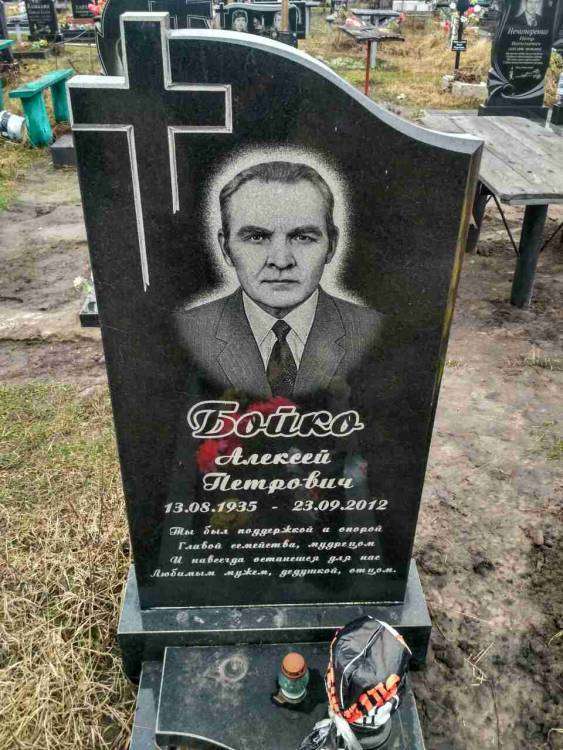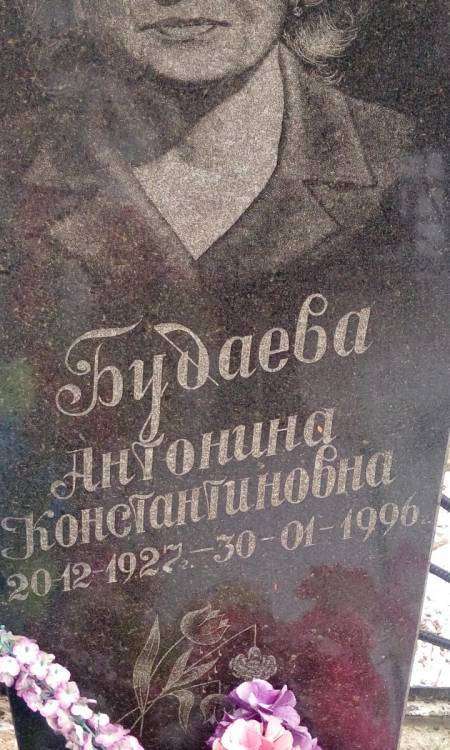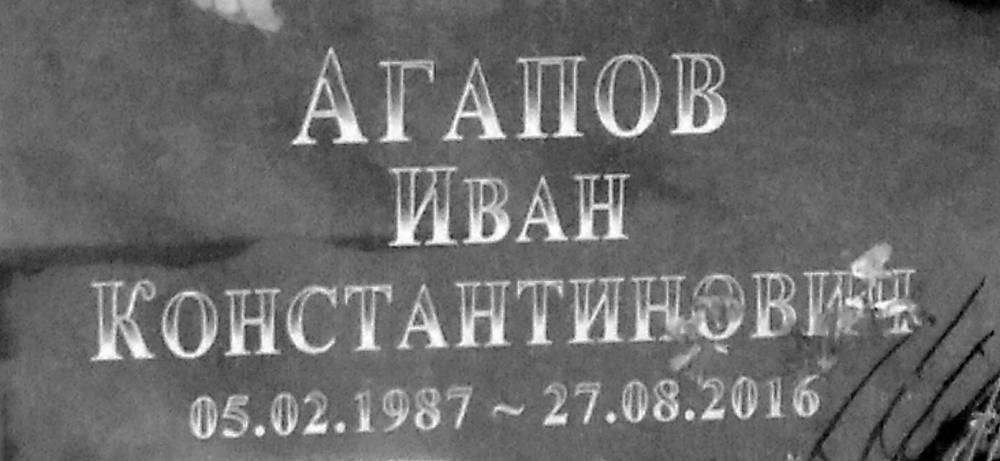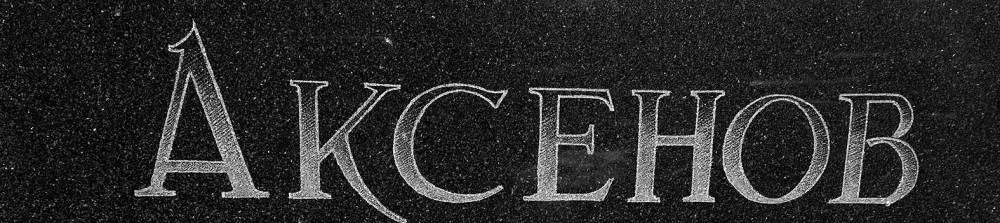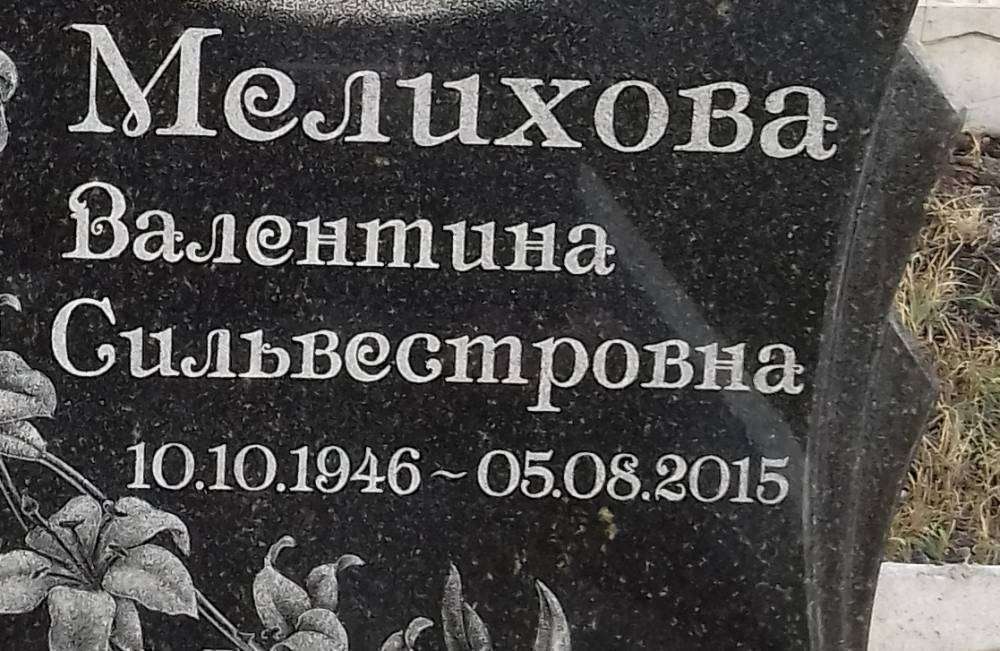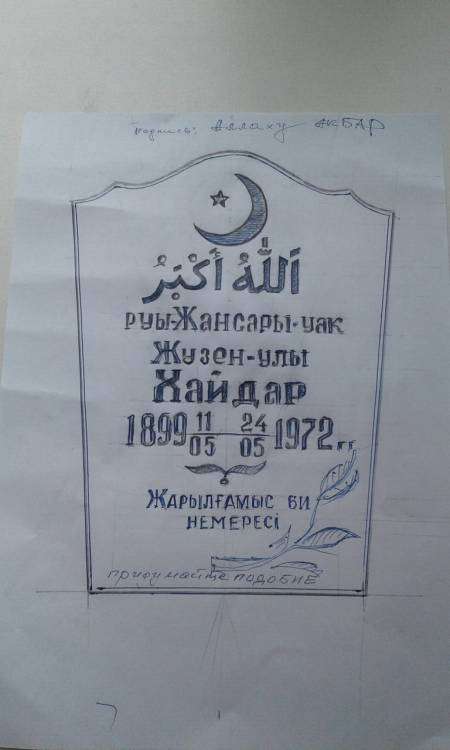
Помогите найти шрифт!
Саид держите нашёл
1Isadora M Bold
Но форум читать надо. Яша уже давным-давно ответил
Выручайте коллеги!
Похож, но не он. Сам весь вечер лопатил сеть. Походу это ручной.
Подскажите кто знает? Что за шрифт на памятнике. Нужно делать второй, а шрифт подобрать не можем
Боярский называется шрифт
Сам всё перелопатил и ни чего не нашёл.ПОМОГИТЕ ПОЖАЛУЙСТА.
Может кому попадался такой шрифт, подскажите пожалуйста
100% - ручной!!!
Хорошо, спасибо, могу ли я узнать по чем Вы определяете ручной шрифт или нет? (хотя сдесь наверное 'в' уж слишком выделяется)
Читайте вот здесь:
Подскажите какой похожий есть шрифт на этот. Заранее спасибо.
Сам нашел, если кому интересно Minion Pro Semibold Disp
montypyton это таймс
Читайте вот здесь:
Нужен такой шрифт подскажите где найти кто знает
В тырнете  Ampir - Deco называется
Добрый вечер, что то подобное подскажите пожалуйста
Шрифт называется "Шрифт, выполненный ручником"
SaNDJorj не совсем верно.
это его разновидность.
называется "шрифт, выполненный криворуким ручником"